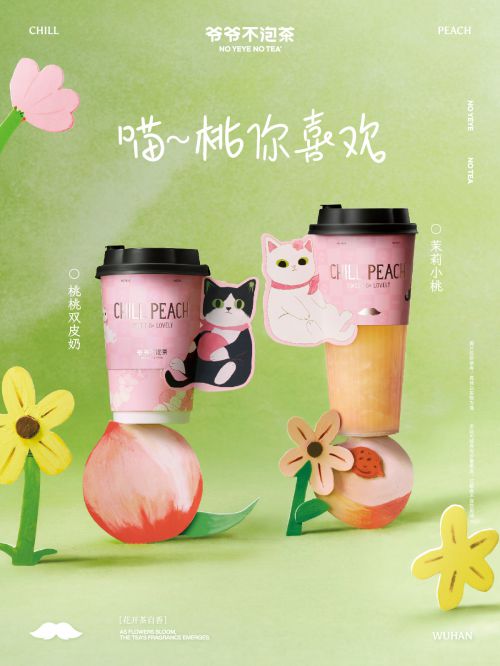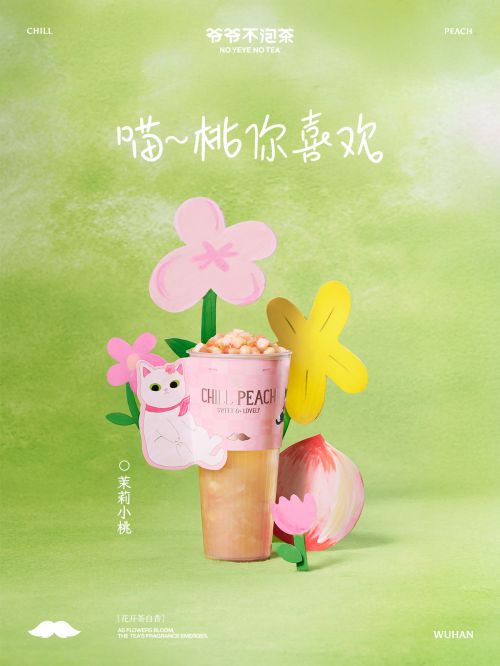
字由转转
一款充满个性和文艺气息的字体,它通过手写笔迹和勾线装饰展现出独特的美感。字体线条流畅,笔画清晰,同时勾线装饰为字体增添了一份灵动和活力。勾线手写体适合在各种场合中使用,如签名、书法、文字设计、信件和日记等,能够带来亲切、自然的视觉效果,同时彰显个性化和艺术风格。这种字体在商业广告、店铺招牌、名片设计等领域也有着广泛的应用,能够为品牌和产品增添独特的艺术魅力和个性化特色。